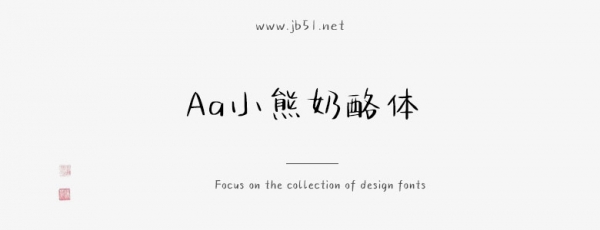
Aa小熊奶酪體是由Aa字庫(kù)出品的字體,這款字體筆觸略細(xì),書(shū)寫(xiě)流暢,略顯可愛(ài),適合應(yīng)用于藝術(shù)設(shè)計(jì)、平面宣傳設(shè)計(jì)、網(wǎng)頁(yè)設(shè)計(jì),書(shū)法字帖等領(lǐng)域,需要的朋友可以前來(lái)本站下載。